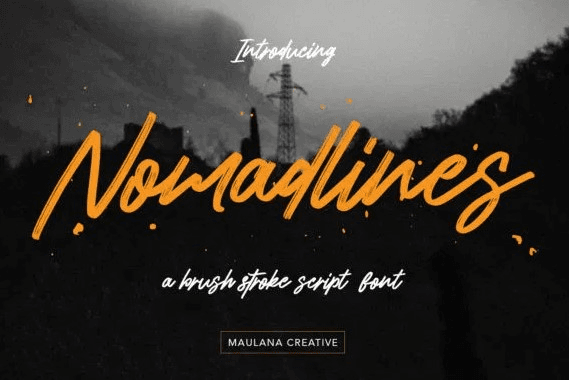
Nomadlines Font
Nomadlines - это скоропись и смелый рукописный шрифт, созданный, чтобы придать стильный штрих вашим заголовкам и логотипам проектов.
Этот шрифт читается как сильный, уверенный и динамичный и может добавить тонны ностальгического характера вашим дизайнам.
Nomadlines - это скоропись и смелый рукописный шрифт, созданный, чтобы придать стильный штрих вашим заголовкам и логотипам проектов.
Этот шрифт читается как сильный, уверенный и динамичный и может добавить тонны ностальгического характера вашим дизайнам.